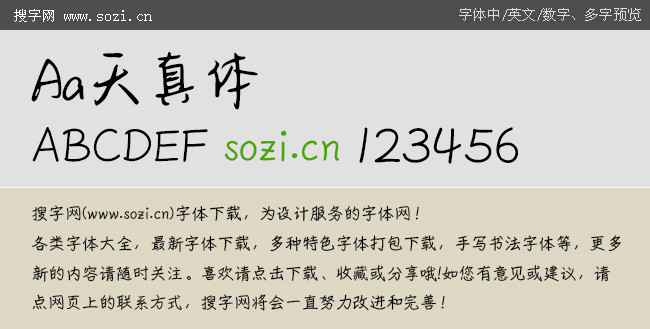
Aa天真體
搜字網(wǎng)給大家提供一款A(yù)a天真體中文字體下載,這是一款手寫風(fēng)格的書法字體,字體書寫自如,并且具有個(gè)性,適合海報(bào)設(shè)計(jì)、包裝畫冊等宣傳廣告等應(yīng)用(此字體為個(gè)人非商用版,如需商用請聯(lián)系作者購買版權(quán))。